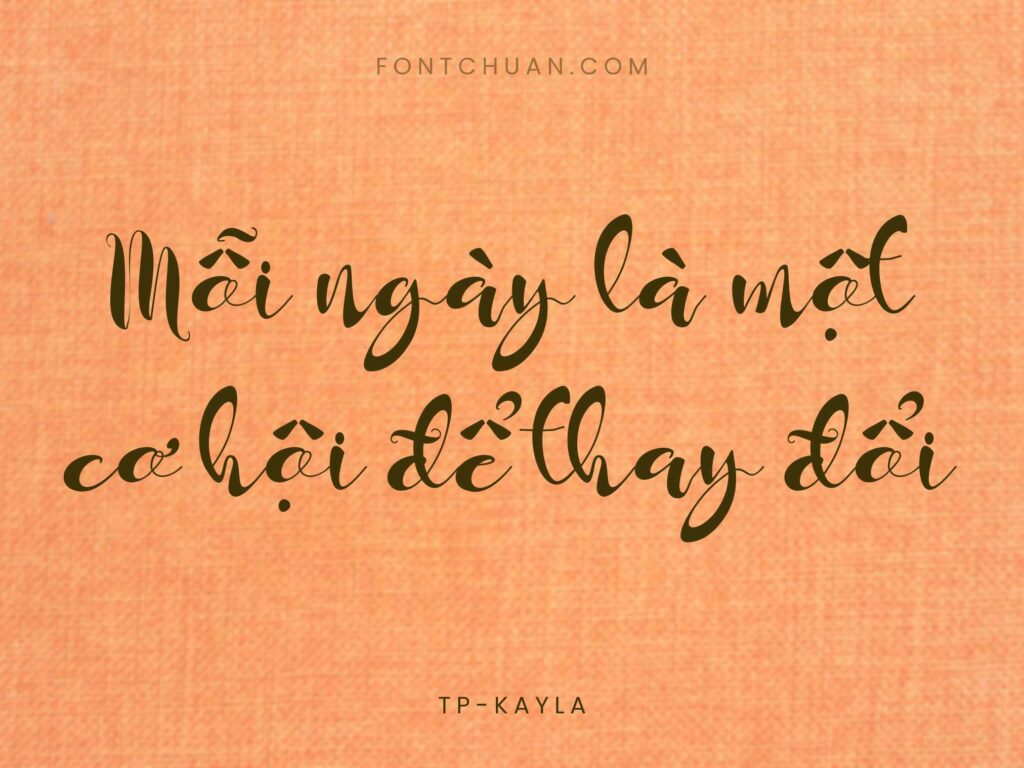
Font TP Kayla Việt Hóa
Tác giả Font: Muhammad Akbar
Kayla là một font chữ viết tay tinh tế và ngọt ngào, được thiết kế bởi Bonjour Type. Font này mang lại cảm giác nhẹ nhàng, thanh lịch và cá nhân hóa, phù hợp cho các thiết kế thiệp mời đám cưới, thiệp chúc mừng hoặc bất kỳ dự án nào cần sự lãng mạn và tinh tế. Với phong cách uyển chuyển và nghệ thuật, Kayla cũng có thể được ứng dụng như một Font cổ trang hoặc Font chữ thư pháp, đem lại vẻ hoài cổ, trang trọng và giàu tính thẩm mỹ cho các dự án mang dấu ấn cá nhân hoặc nghệ thuật. Font đã được Việt hóa để hỗ trợ tiếng Việt bởi Tuỳn Pucca, giúp mở rộng phạm vi sử dụng cho người dùng Việt Nam. Font này được sưu tầm và chia sẻ bởi thành viên của Font Chuẩn, đáp ứng nhu cầu sử dụng trong các dự án thiết kế đa dạng.
Đặc điểm thiết kế của Kayla bao gồm các nét chữ mềm mại và uyển chuyển, tạo cảm giác thân thiện và gần gũi. Font này phù hợp cho các ứng dụng như thiết kế thiệp mời, logo, thương hiệu cá nhân và các dự án sáng tạo khác. Các ngành nghề phù hợp bao gồm giáo dục, nghệ thuật và thiết kế đồ họa.